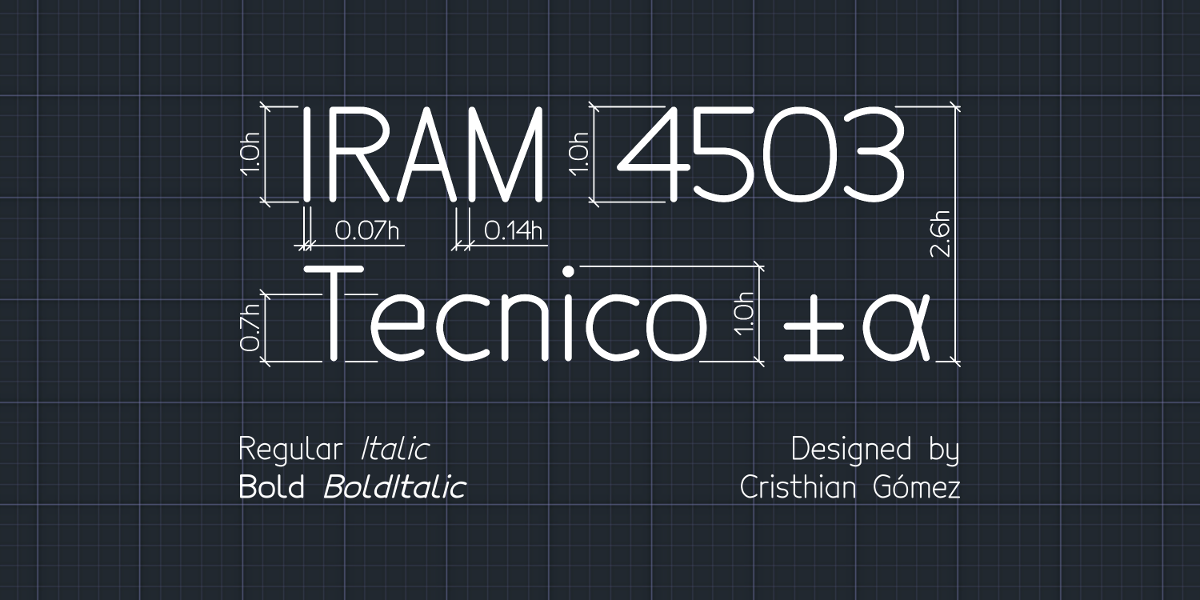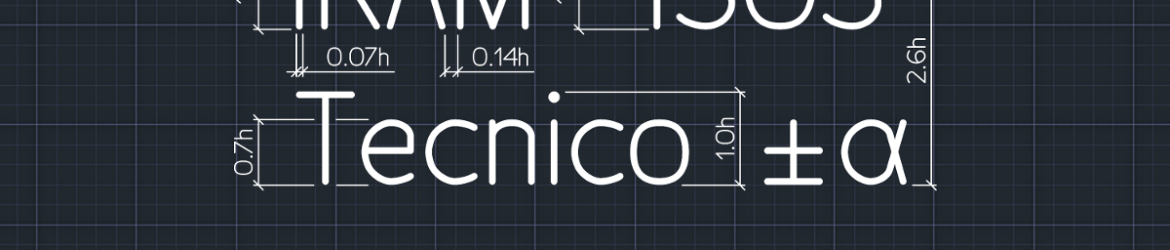
A fonte Tecnico Typeface é uma seleção cuidadosa do tipo de sans-serif que se destaca na categoria das fuentes de escrita sem serif, especialmente adequada para aplicações técnicas como planilhas e desenhos técnicos. Essencialmente, representa o padrão estabelecido em escrita utilizada nos documentos arquitetônicos e de engenharia. Desenvolvida de acordo com as indicações da IRAM 4503, Tecnico é a escolha perfeita para quem busca uma fórmula elegante e funcional. Seu design simples e limpo se ajusta perfeitamente em qualquer layout, fornecendo legibilidade clara e estruturas uniformes. Seu forte enquadramento e facilidade de leitura são excelentes opções para designers, gráficos ou até mesmo arquitetos que procuram uma fórmula eficaz para a escrita técnica.